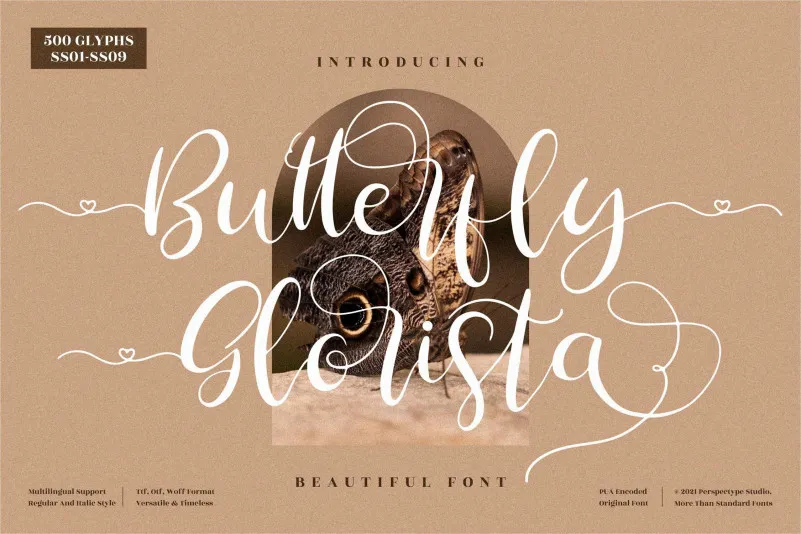
Butterfly Glorista Font – Download Grátis
A Butterfly Glorista Font é uma escolha perfeita para quem busca um visual elegante e sofisticado em designs digitais. Com seu traço levemente à mão, esta fonte traz consigo um toque único que certamente vai deixar qualquer projeto de design com o toque final desejado. Seja para gráficos de newsletter ou capas de livros, a Butterfly Glorista adicionará um brilho luxuoso e uma personalidade distintiva à sua produção. O fato de ser PUA codificado significa que você terá facilidade em acessar todos os encantadores caracteres e ligaturas, tornando essa fonte não apenas incrível no papel impresso, mas também perfeita para criações digitais.